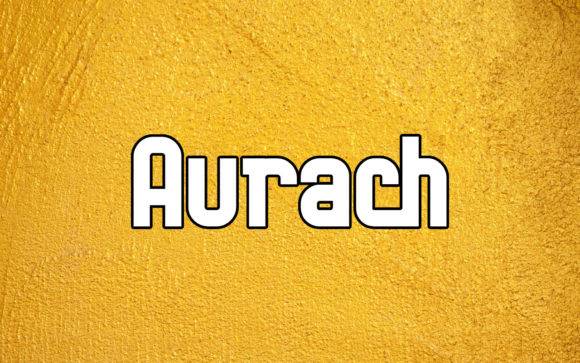
Fonte Aurach para títulos, pôsteres e projetos de identidade visual.
Dê destaque aos seus projetos com a fonte Aurach . Esta fonte de exibição moderna, com letras grossas e um design limpo, é ideal para projetos de branding, como logotipos, impressão de camisetas e muito mais. Sua versatilidade e ousadia trazem criatividade a qualquer design.
- Design moderno com letras grossas
- Perfeito para logotipos e identidade visual.
- Fonte de exibição limpa